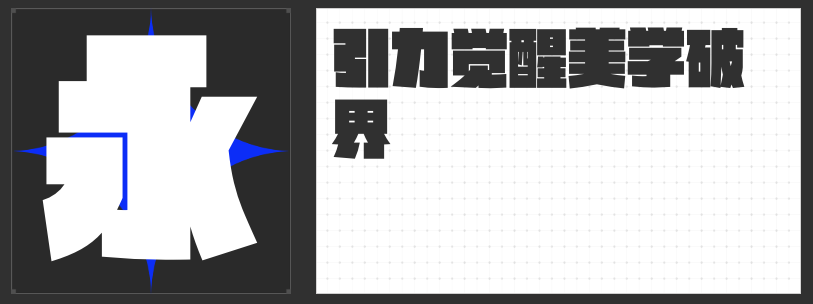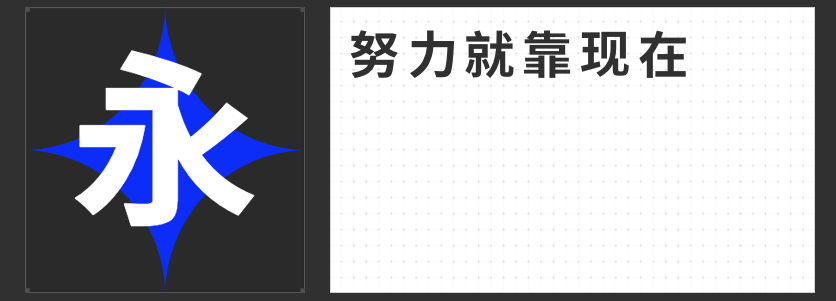
四款硬核字体,打造沉浸式游戏世界观
在RPG游戏设计中,字体不仅是信息传递的载体,更是构建世界观的关键元素。以下四款专为现代游戏场景优化的字体,以独特的美学语言强化视觉叙事,助力开发者塑造独特的游戏氛围。
一、励字暴风简 超级黑
这款字体以梯形笔画解构传统黑体,横竖笔画呈不对称分布,撇捺处加入锐角切割。在科幻题材游戏中,其不规则的几何美感与霓虹光影完美契合,尤其适合机甲界面、黑客终端等UI设计。超黑字重确保在4K分辨率下依然保持细节张力,让玩家瞬间代入未来都市的赛博空间。
二、励字跨界黑简 超级黑
拥有90%字面率的跨界黑简,将粗犷直线与流畅曲线融合,收笔处采用斜切处理,形成独特的块面节奏。其硬朗气质非常适合魔幻题材的主线任务标题,在龙与城堡的场景中,字体自带的铠甲纹理质感能强化史诗叙事。建议搭配渐变材质使用,让标题文字如石碑般矗立于虚拟世界。
三、 字圈也字时代黑体
这款字体复刻早期铅字印刷的喇叭口装饰,在蒸汽朋克场景中如同齿轮间的机油痕迹。其笔画端点的装饰性开口,与齿轮、管道等机械元素形成视觉对话,适合用于工作坊界面、发明家手札等场景文字。在复古棕色调的UI中,能唤起玩家对工业革命时代的想象。
四、励字励黑简
这款超粗方体字去除所有装饰性笔画,以绝对均匀的线条构筑数字迷宫。笔画超粗而有力,字形结构严谨,朴素大方,稳重醒目,特点是没有衬线装饰,字面呈正方形的超粗壮字体;笔画无粗细变化,起笔处为方头,折笔处无字肩。其清晰可读的特性,成为了游戏设计的首选。
四款字体构建了从未来都市到魔法王国,从蒸汽机械到像素迷宫的美学坐标系。开发者可根据游戏基调自由组合:暴风简塑造科技叛乱感,跨界黑简强化史诗张力,也字时代黑体注入复古温度,励黑简坚守像素信仰。当字体设计与游戏叙事同频共振时,虚拟世界便拥有了真实的重量与质感。